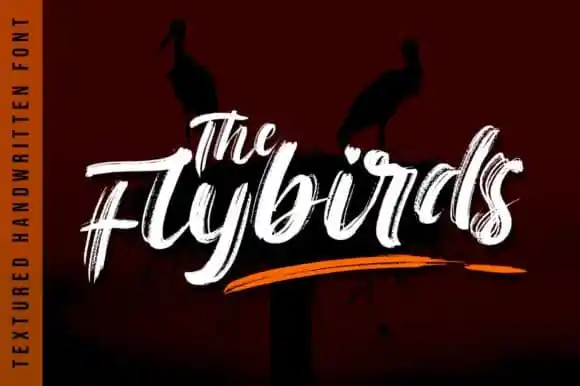
The Flybirds Brush Font – Fonte Grátis
The Flybirds Brush Font
A fonte ‘The Flybirds Brush Font’ é uma tipografia brushscript que combina a riqueza multilíngue com destaque e swashes. Manufacturada pela Green Adventure Studio, ela se destaca por seu estilo manuscrito forte e casual. Cada traço foi cuidadosamente desenhado para mostrar um fluxo fluido e armonia, tornando-a ideal tanto para projetos de marca como para roupas, anúncios, embalagens de produtos ou qualquer aplicação que exija uma fonte com estilo brusco. Com sua versatilidade multilinguística e design cuidadosamente elaborado, ‘The Flybirds’ oferece um toque único e sofisticado a qualquer projeto visual.